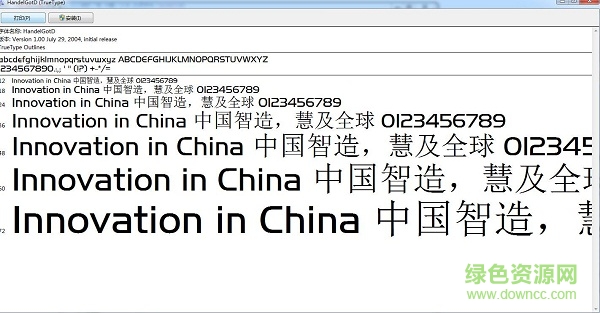
handelgotd字体包收录了handelgotd bold和handelgotd regular两款无衬线字体,字体特征鲜明,弧线漂亮,可以电子产品、平面设计、海报设计等领域,需要的朋友快来下载吧!
它以几何学的方式确立汉字的基本结构(它是构建性的,而非书写性的),其均匀的笔划宽度和平滑的笔划弧度表现出一种稳定的、充满机器意味的无时间性及共时性特征!
有相同的曲率;
笔直的线条;
锐利的转角。